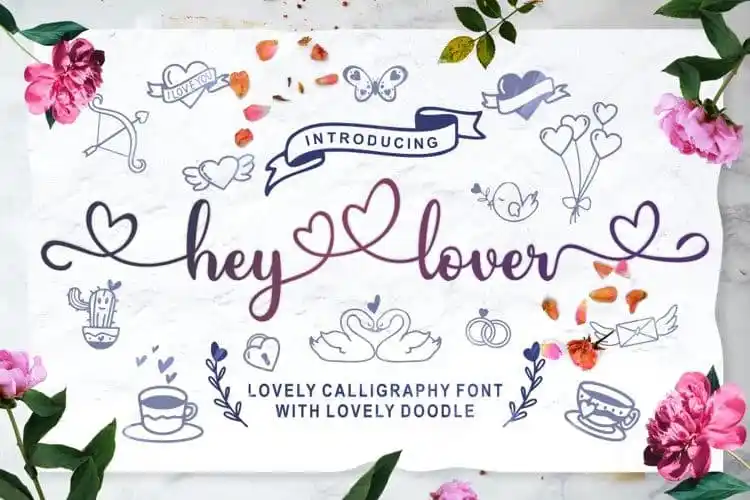
Hey Lover Calligraphy Font – Fonte Grátis
Hey Lover Calligraphy Font
A Hey Lover Calligraphy Font é uma elegante tipografia script que se destaca pela sua delicadeza e flexibilidade para diversas utilizações. Esta fonte é ideal para adicionar um toque sofisticado a eventos como festas de casamento, aniversários ou até mesmo para estampar produtos fashion com toques femininos e bem cuidados. O design foi realizado por Letter Nun em 99designs e incorpora uma nova abordagem moderna para o estilo moderno da chamada letra. Com essa fonte, designers podem criar composições equilibradas com estilo de garras, além de manter um aspecto atraente mesmo com os caracteres básicos. Para maior conveniência, inclui-se uma versão itálica ou inclinada para facilitar a personalização dos materiais impressos e tornando o processo de criação ainda mais fácil. Esta fonte é perfeita para quem busca um toque único e autêntico em sua identidade visual ou se dedicam ao mundo da moda, beleza e salões. Combinada com os detalhes finos e a delicadeza do estilo calligráfico, Hey Lover é uma escolha inteligente para designers e criativos que procuram um toque romântico e sofisticado em seus projetos.